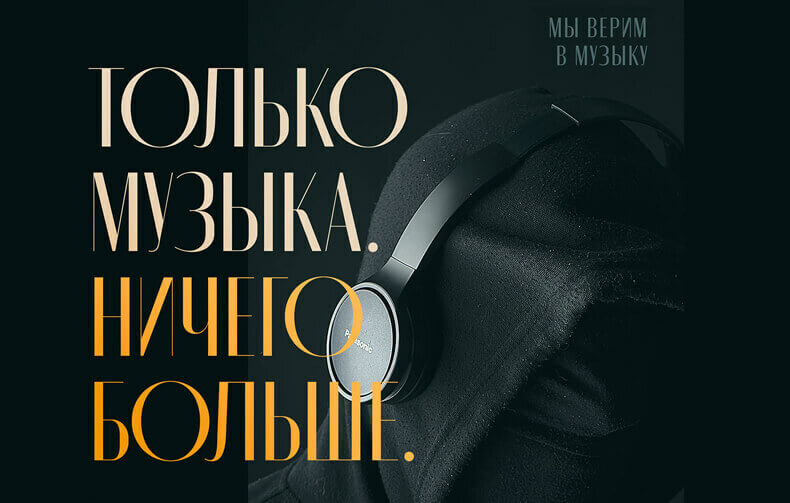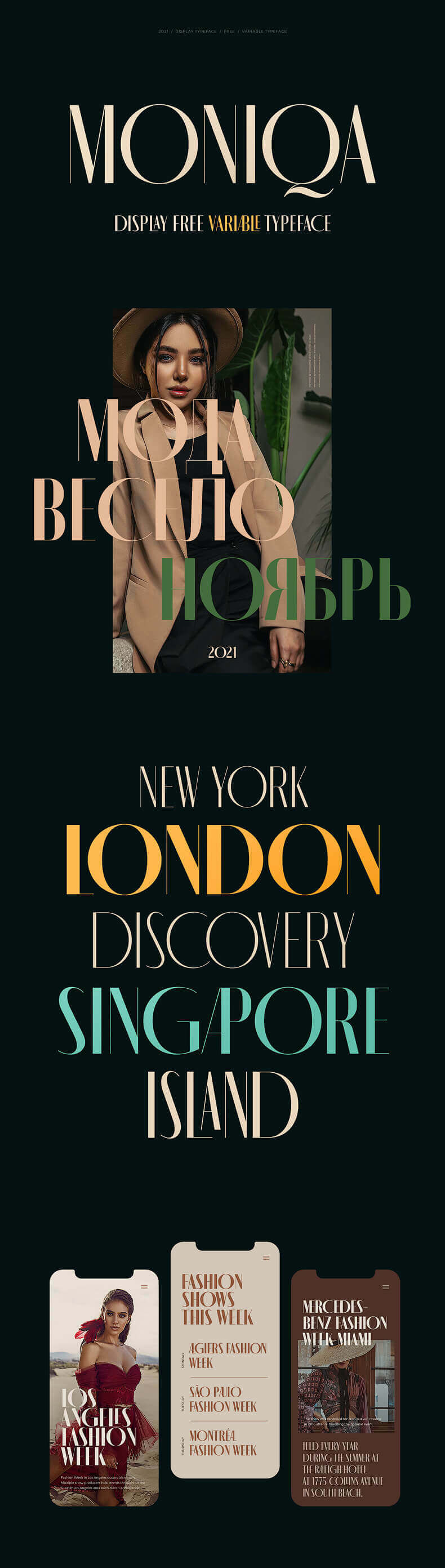
Кириллический шрифт - MONIQA
Семейство шрифтов MONIQA — это кириллический шрифт с поддержкой латиницы с необычным узнаваемым стилем и с множеством начертаний.
УМОЛЯЮ, кто-нибудь, ПОЖАЛУЙСТА, расскажите мне как в этом шрифте сделать буквы (о,с,э и тд) круглыми, а не вытянутыми 😵‍💫
Alain Yartseva, 1. Каждое слово на отдельном текстовом слое.
2. Инструмент Текст, вкладка Глифы.
3. На нужном слое выделить нужную букву, найти в Глифах нужный символ, дабл-клик по найденному символу.
4. Символ заменит выделенный.